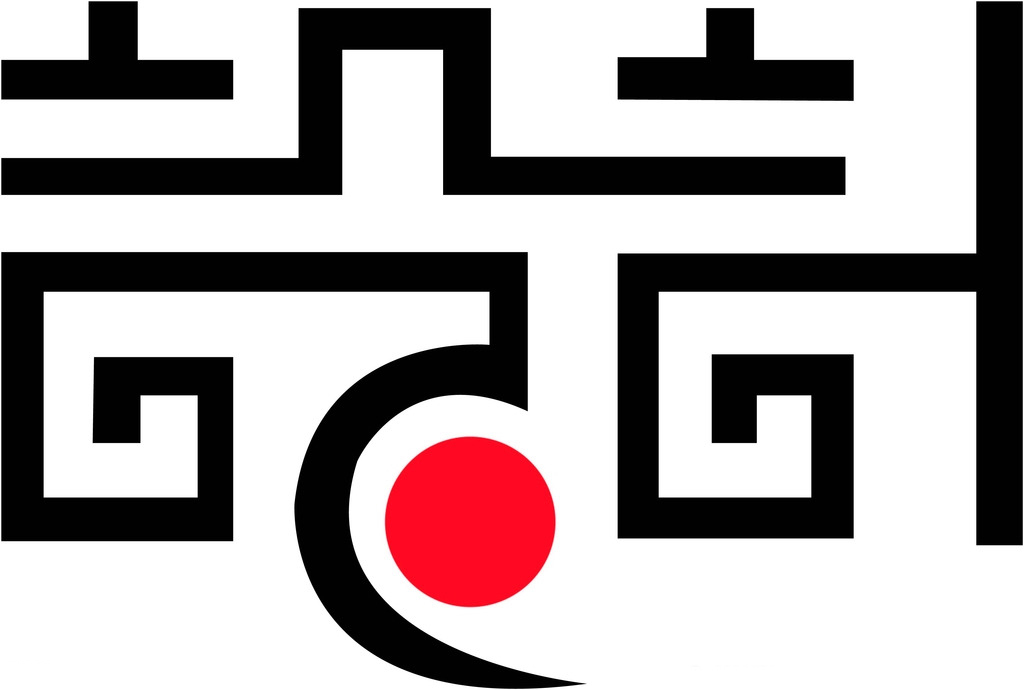
字体设计是一门视觉艺术,它将艺术性与实用性完美地结合在一起。字体设计可以用来传达信息、表达情绪、创造品牌标识,甚至影响人们对世界的看法。
一个精心设计的字体可以使文本更易于阅读、更令人愉快、更有影响力。字体设计是一个复杂的过程,需要考虑许多因素,例如字形、间距、可读性和整体美观。
字体设计的元素
字体设计有许多关键元素,包括:
- 字形:字形是指字母、数字和符号的外观和形状。
- 间距:间距是指字母和单词之间的空间。
- 可读性:可读性是指文本的易读性。
- 整体美观:整体美观是指字体的外观和感觉。
所有这些元素共同创造了字体的外观和感觉。一个有效的字体设计将所有这些元素无缝地结合在一起,创造出一个既实用又美观的字体。
字体设计的重要性
字体设计对各种应用至关重要,包括:
- 品牌标识:字体设计可以在创建独特的品牌标识中发挥重要作用。
- 营销材料:字体设计可以使营销材料更具吸引力和影响力。
- 数字媒体:字体设计可以在数字媒体中用于创建令人愉悦的用户体验。
- 艺术和设计:字体设计可以在艺术和设计领域中用于创造视觉冲击和传达信息。
字体设计是一种强大的工具,可以用来创建视觉冲击、传达信息和创造品牌标识。通过了解字体设计的元素和原则,您可以创建出色的字体,为您的项目增添价值。
结论
字体设计是一门视觉艺术,它将艺术性与实用性完美地结合在一起。一个精心设计的字体可以使文本更易于阅读、更令人愉快、更有影响力。通过了解字体设计的元素和原则,您可以创建出色的字体,为您的项目增添价值。